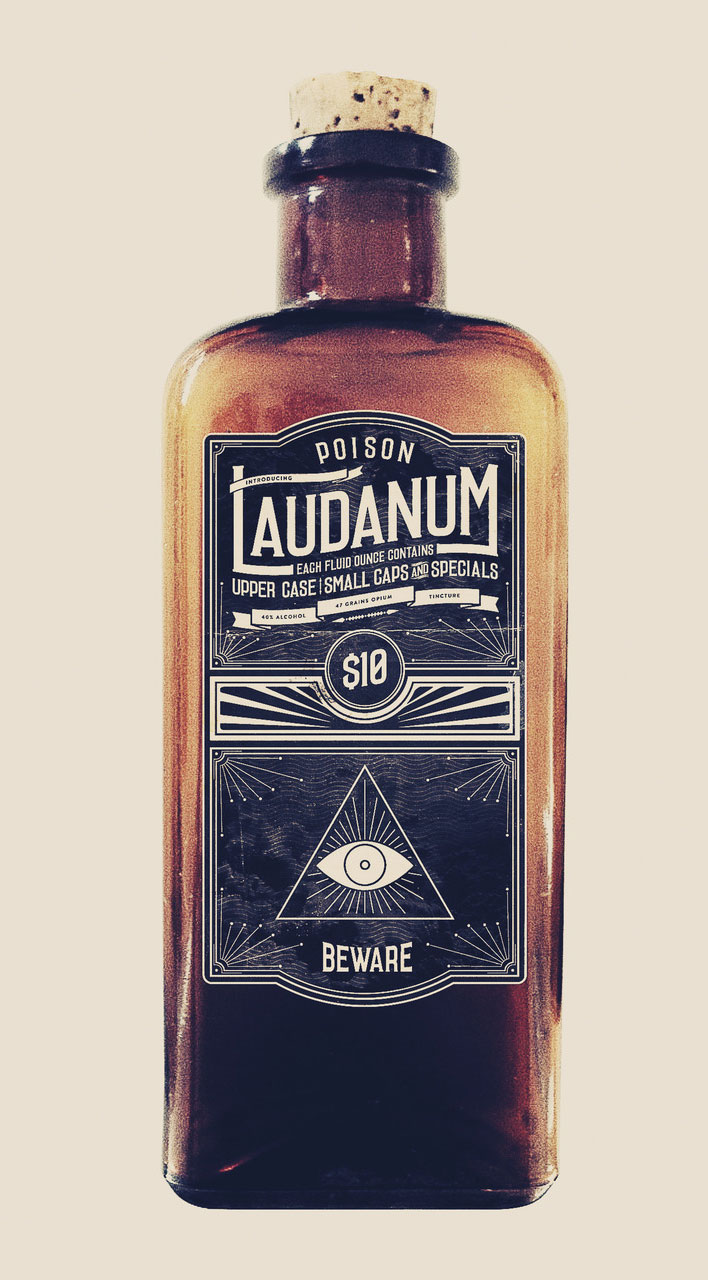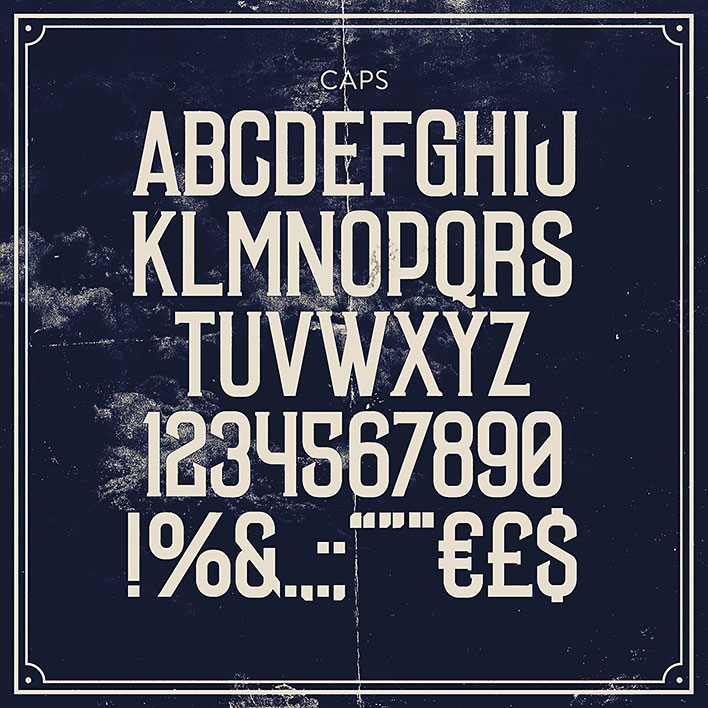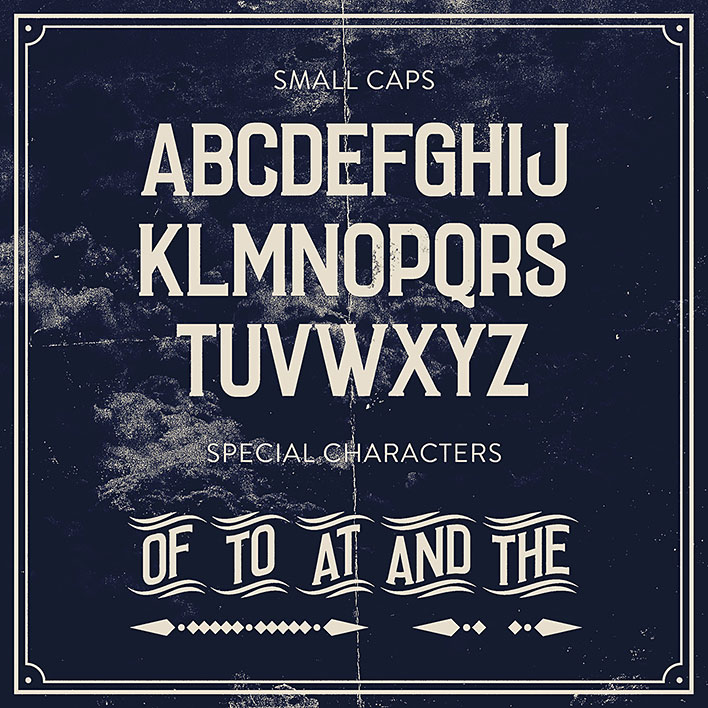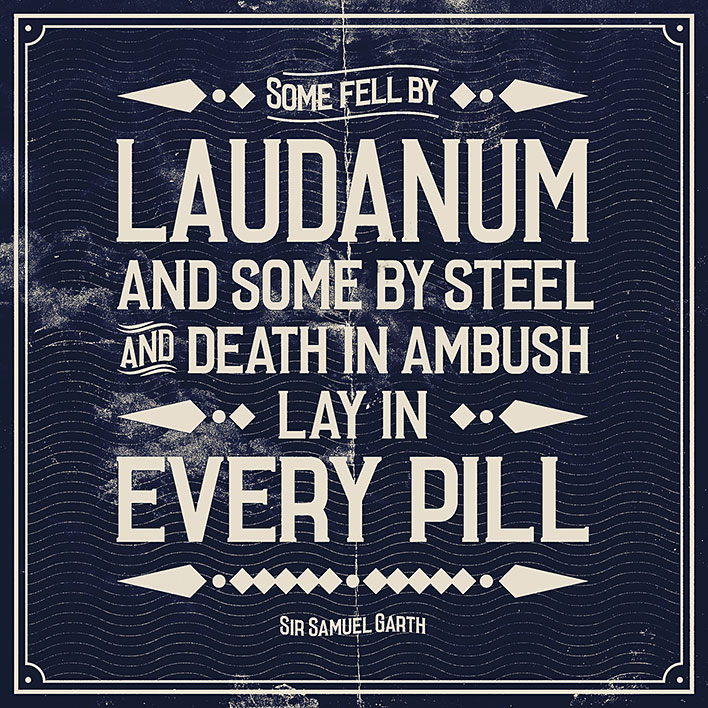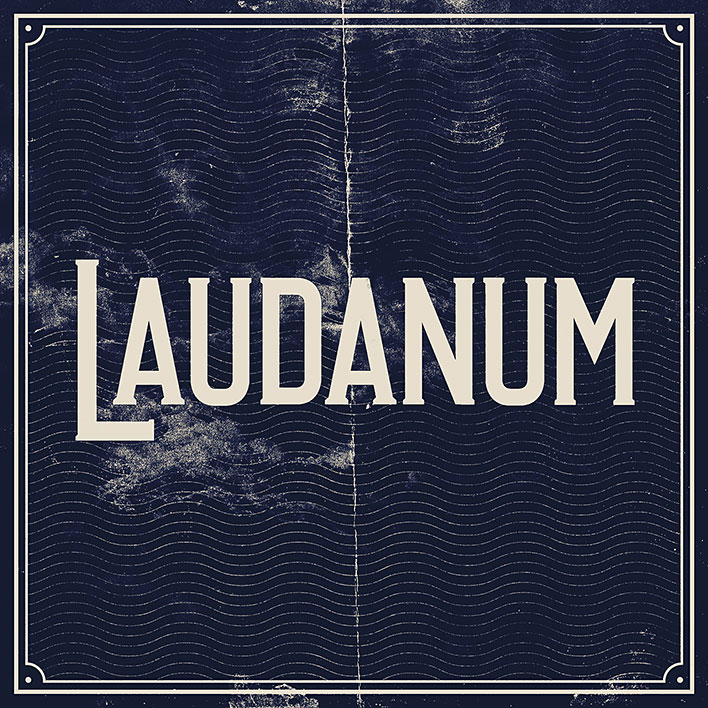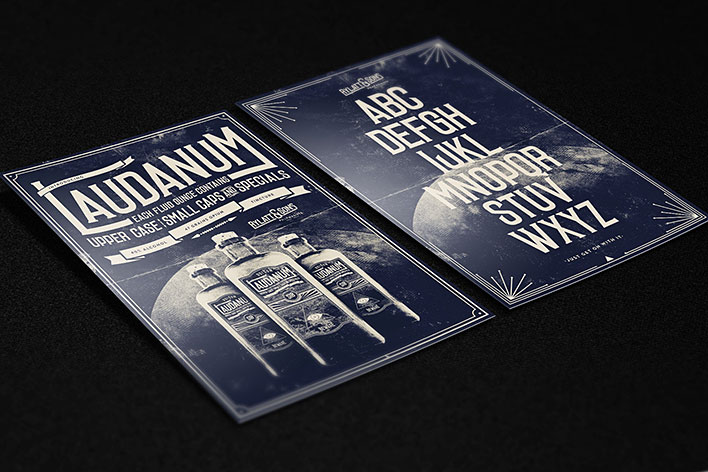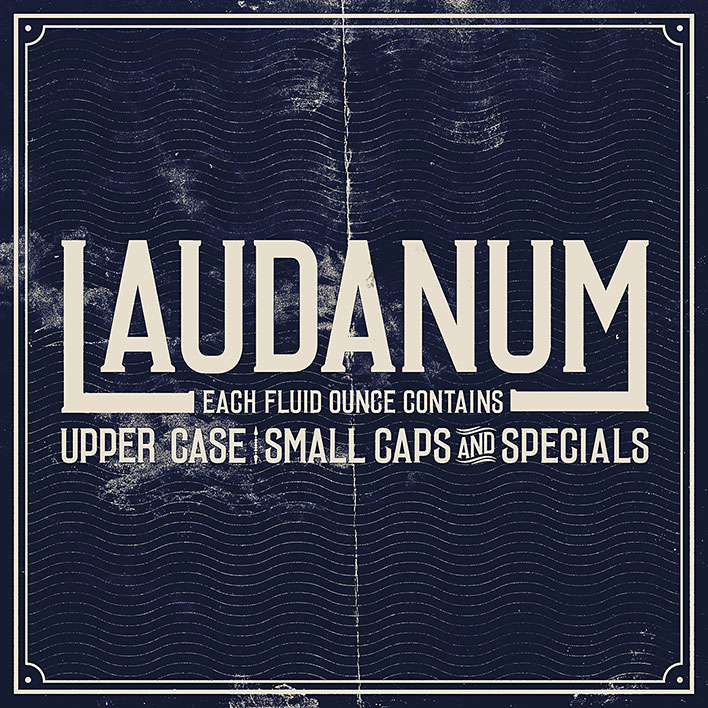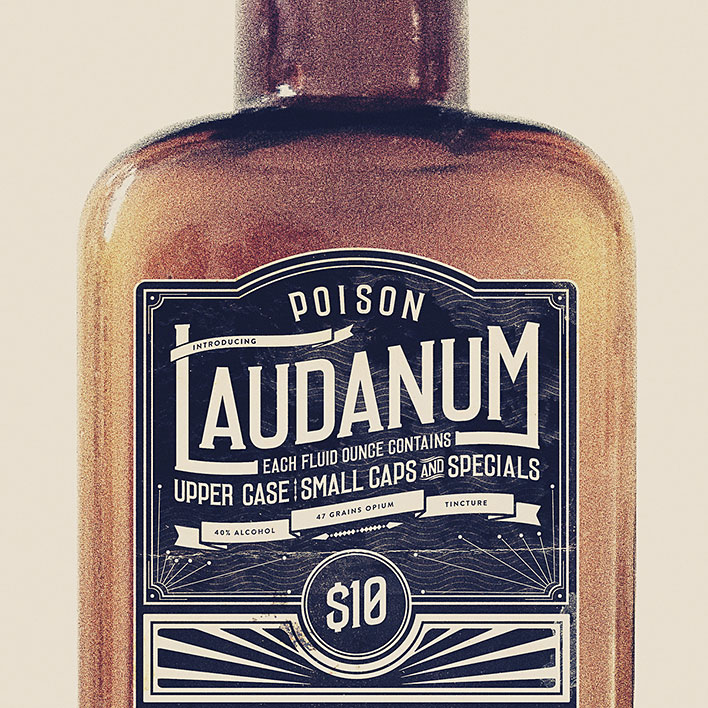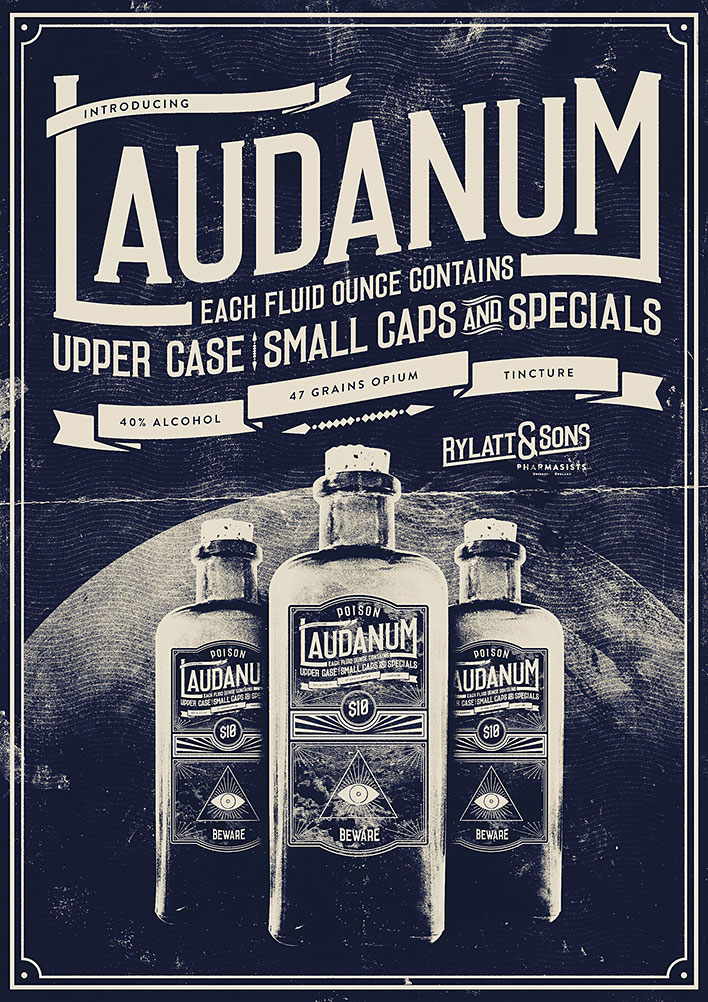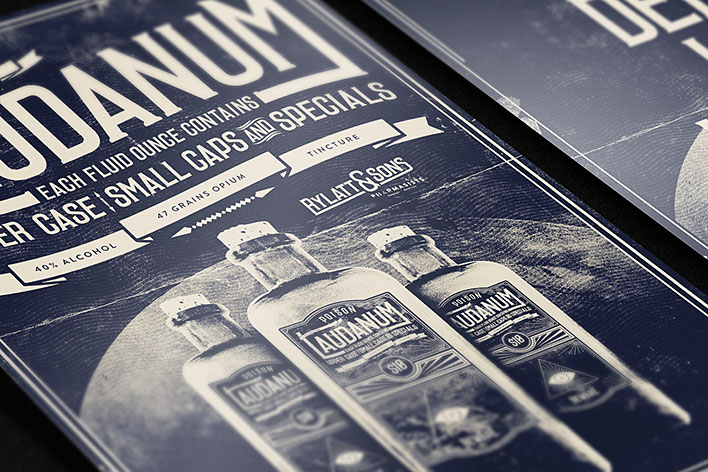
Винтажный шрифт Laudanum
Графический дизайнер Carl Rylatt, вдохновленный плакатными шрифтами XIX века, создал щрифт под названием Laudanum. Цена данного шрифта составляет $10. На самом деле нас не интересует его стоимость, нам понравилась подача с которой автор преподносит свое творение. Работа пропитана старостью и присущим цветовым оформлением. Несомненно, красивая обертка продает (создает) лицо товара, без которой он не был бы воспринят и затерялся среди сотен ретро шрифтов.